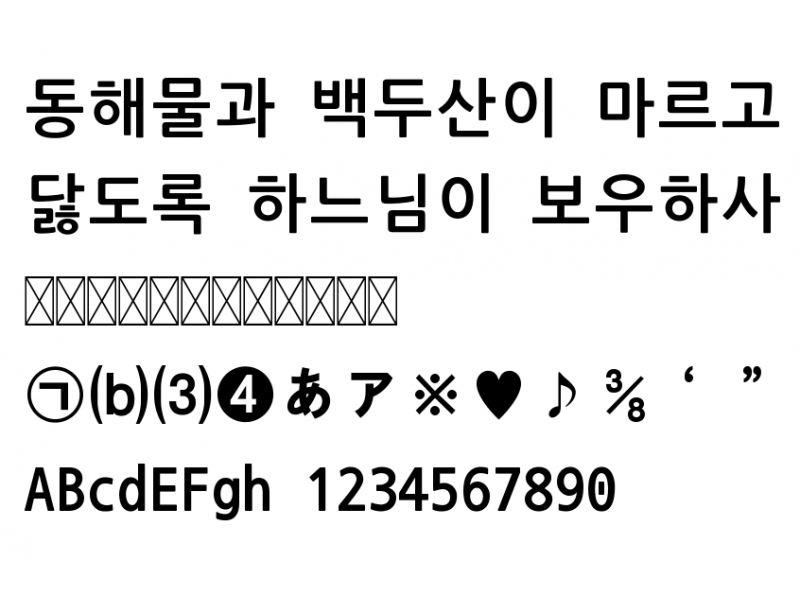
나눔고딕코딩체는 지난 2008년 10월 9일 발표된 나눔고딕을 바탕으로 개발자들의 코딩 환경에 최적화시킨 글꼴이다.
한글, 영문, 일문 문자의 디자인이 되어 있으며 한자는 포함되어 있지 않다. (한자를 표시해야 할 경우 다른 글꼴로 대체) 제어 문자 31자가 포함되어 있다.